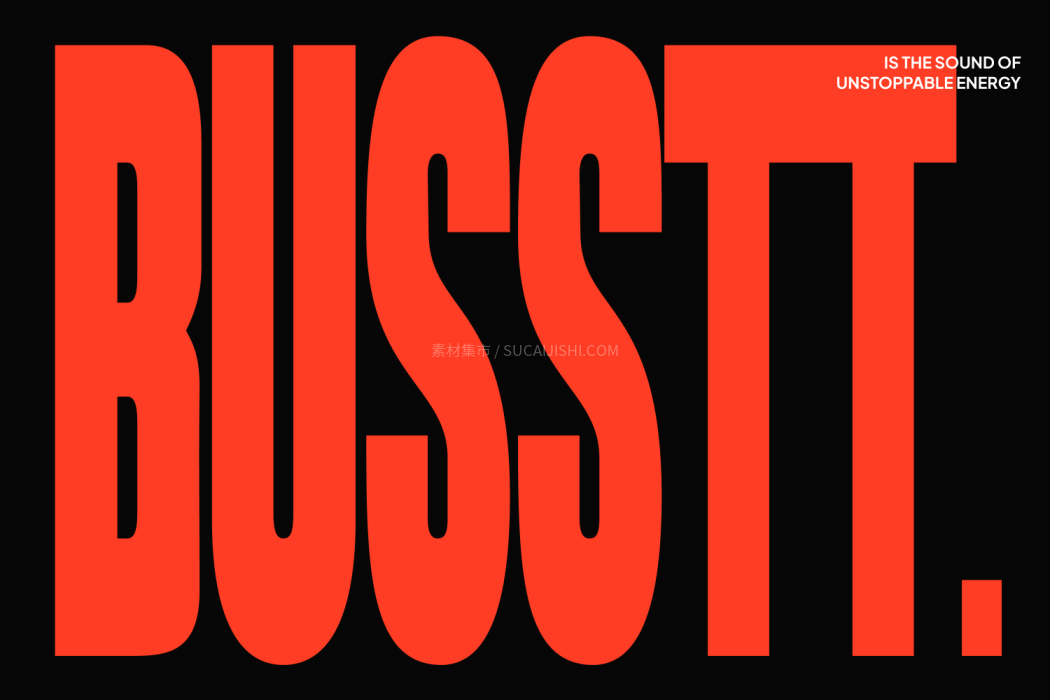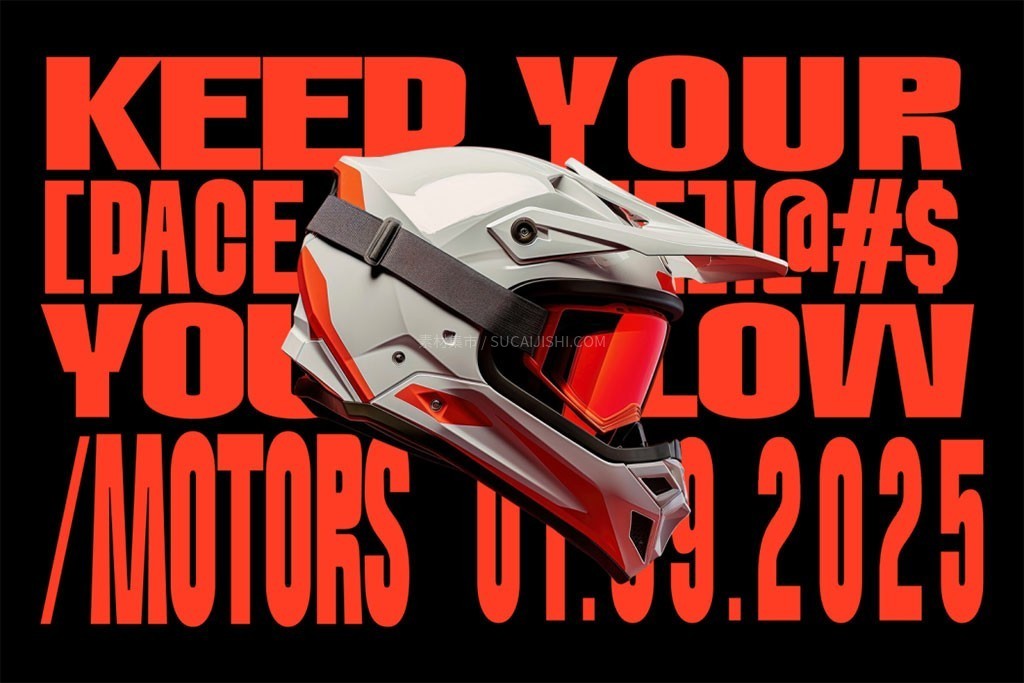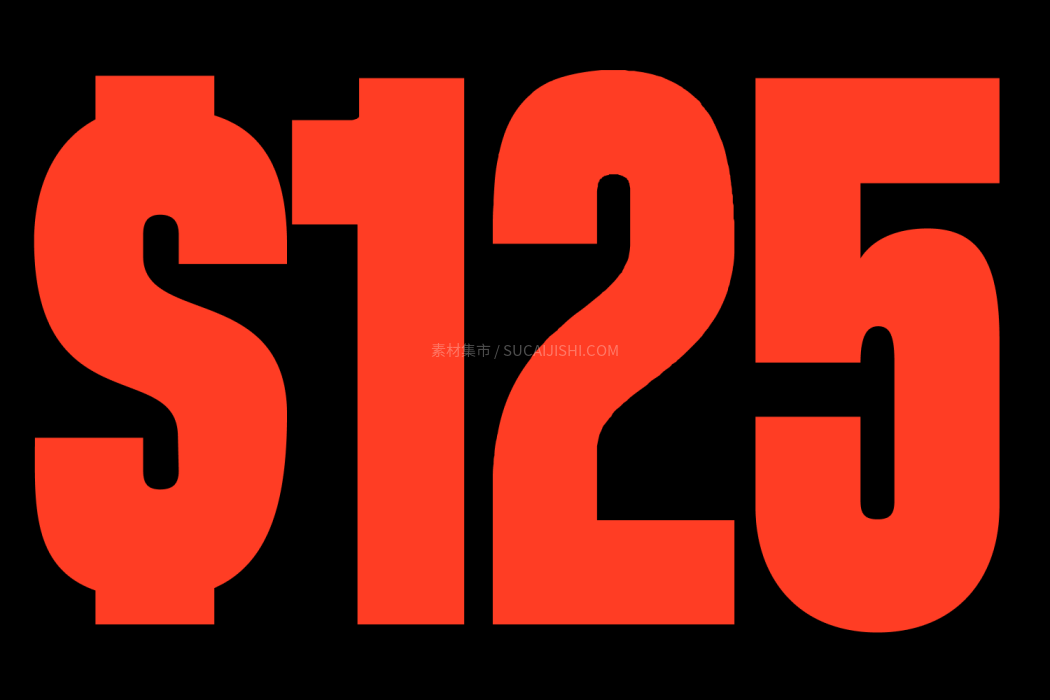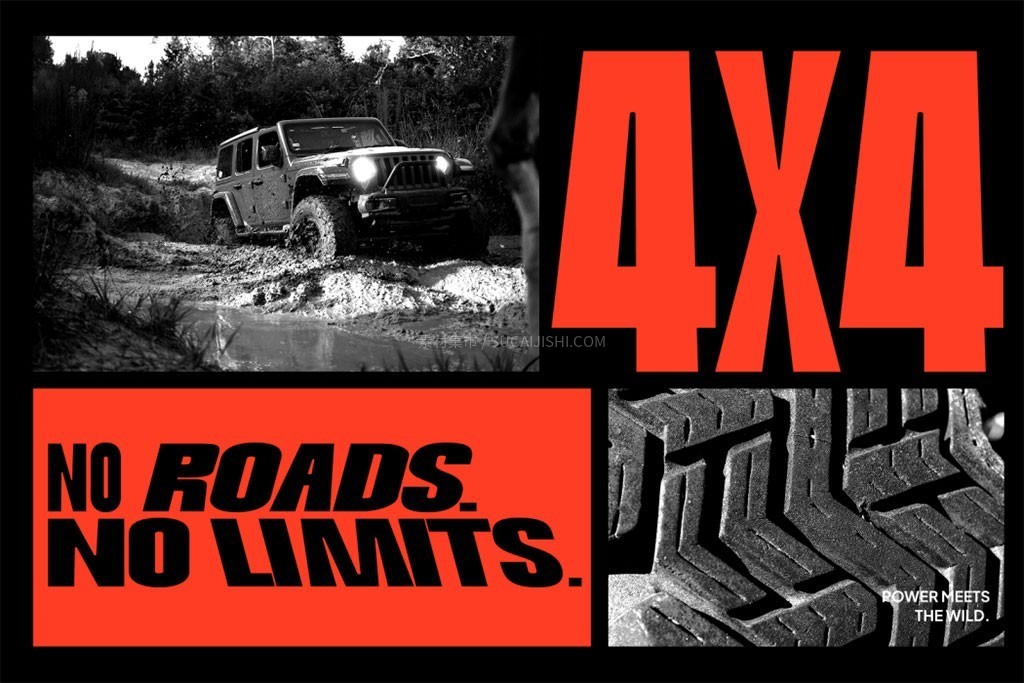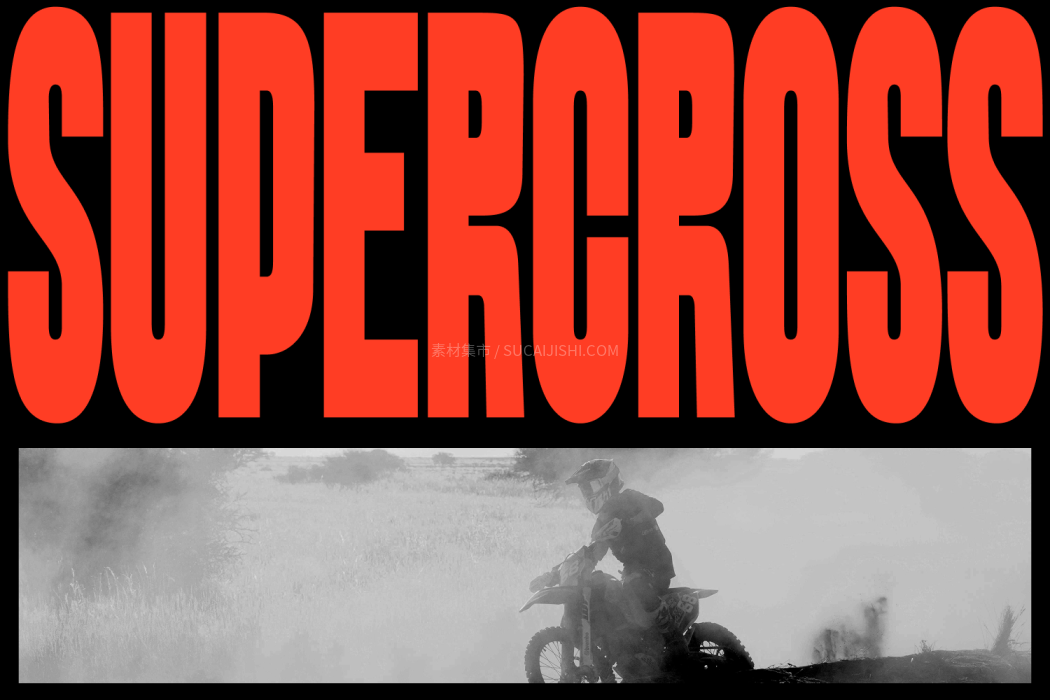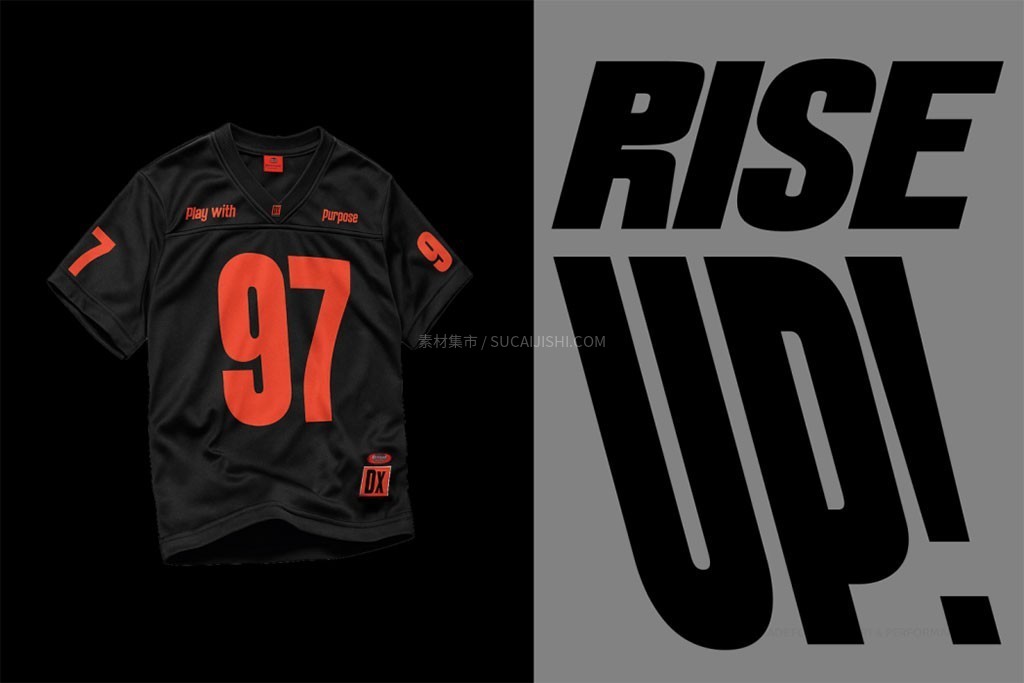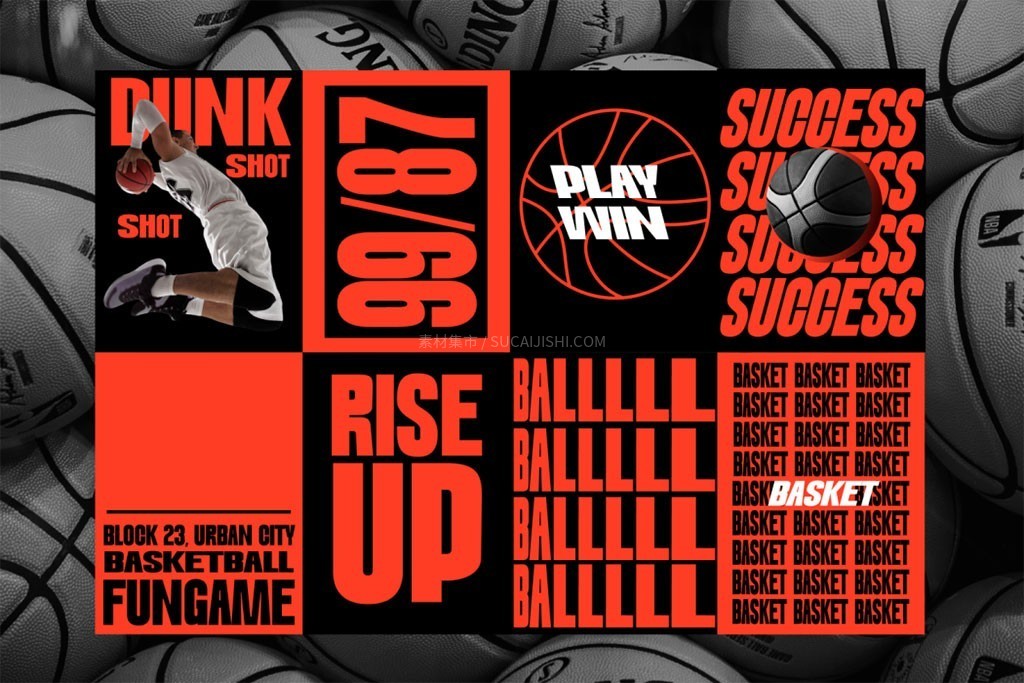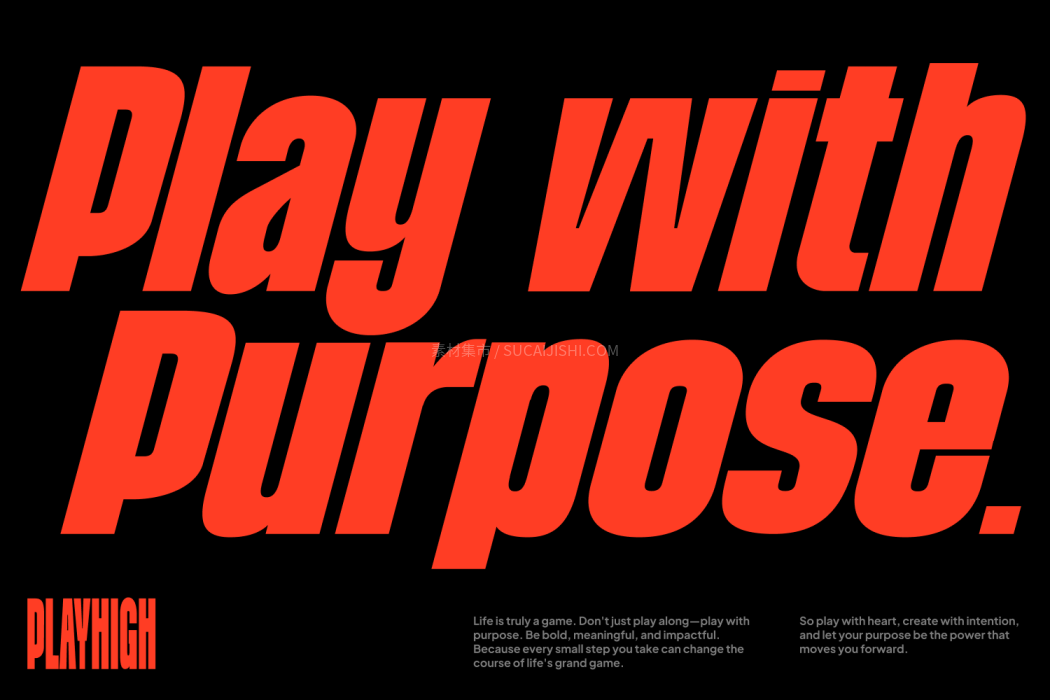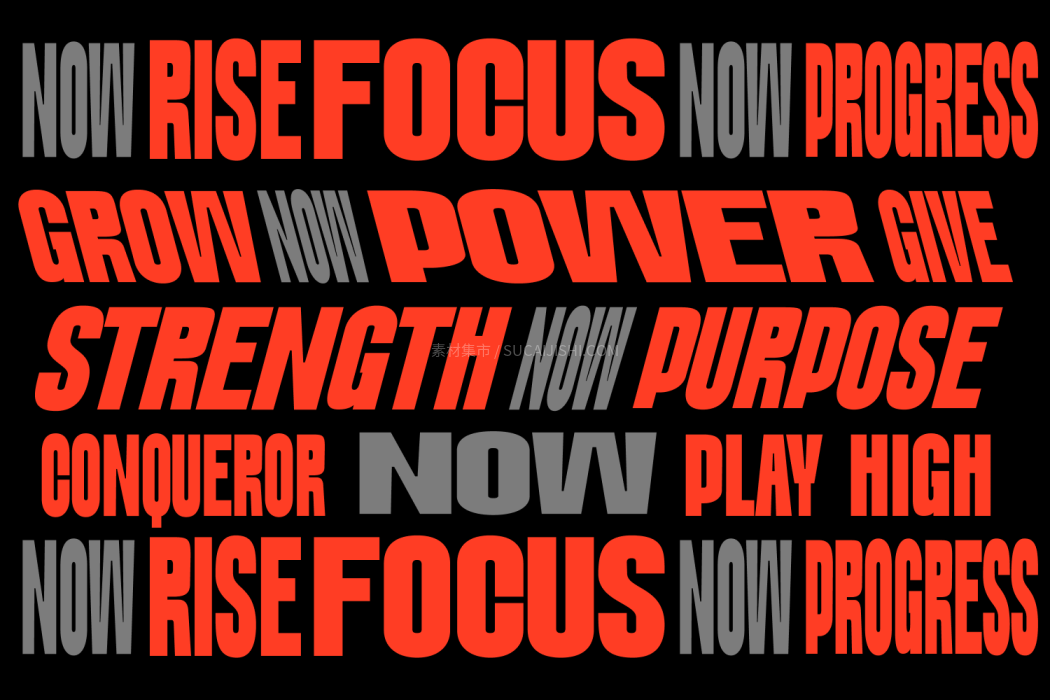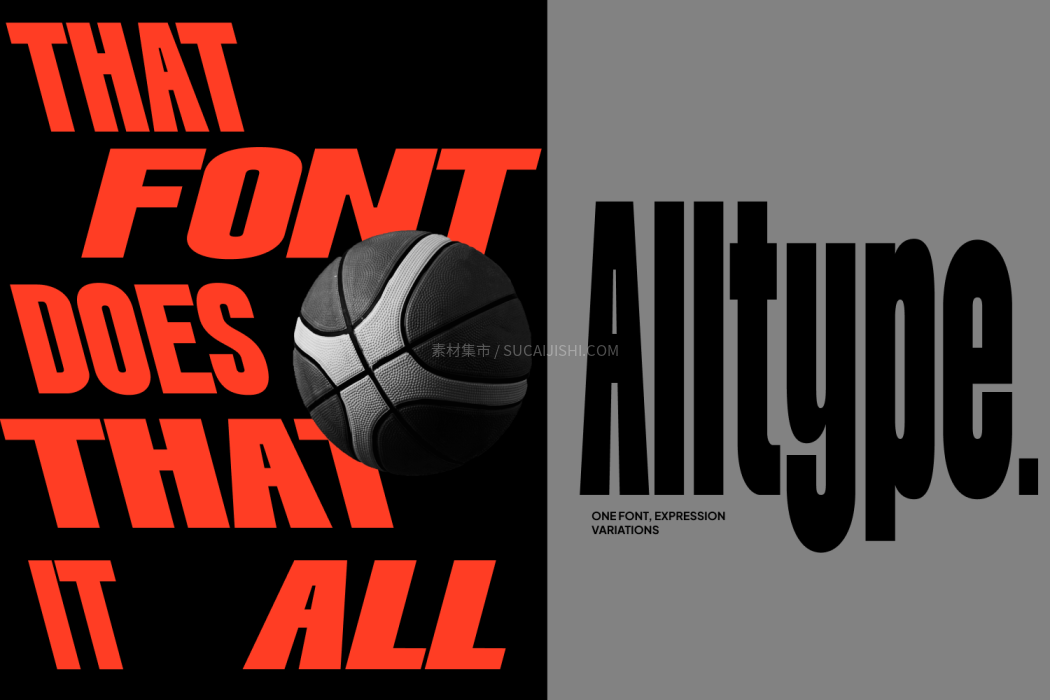
DX Playhigh 可变无衬线字体
DX Playhigh 是一款极具张力和活力的无衬线展示字体,超级适合用来彰显设计个性!它自带多达 21 种样式,涵盖常规、斜体和反斜体,宽度从极窄到超宽无所不包。强大的可变字体技术让你能顺滑无缝地微调字宽和视觉效果。强劲的字形与锐利的几何线条,不仅保证了排版的专业度和易读性,还能为你的设计作品瞬间拉满大胆、前卫的未来感!